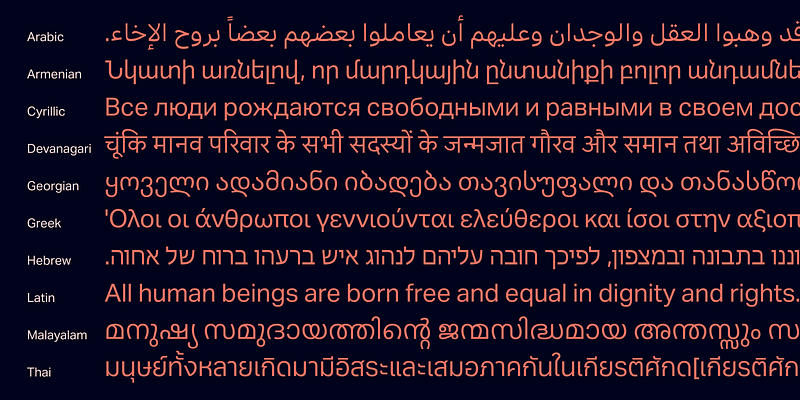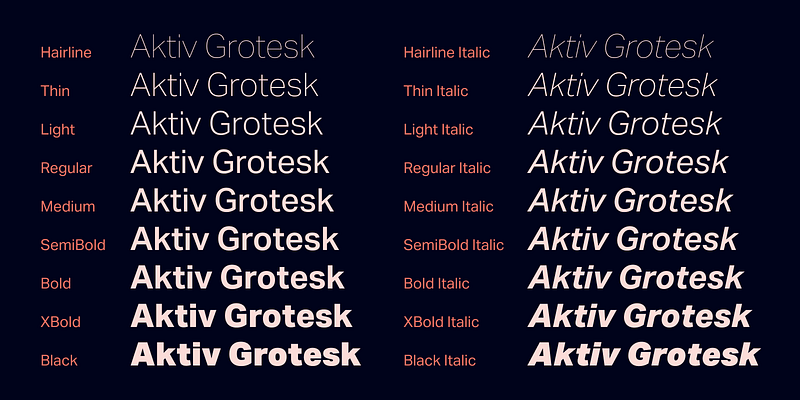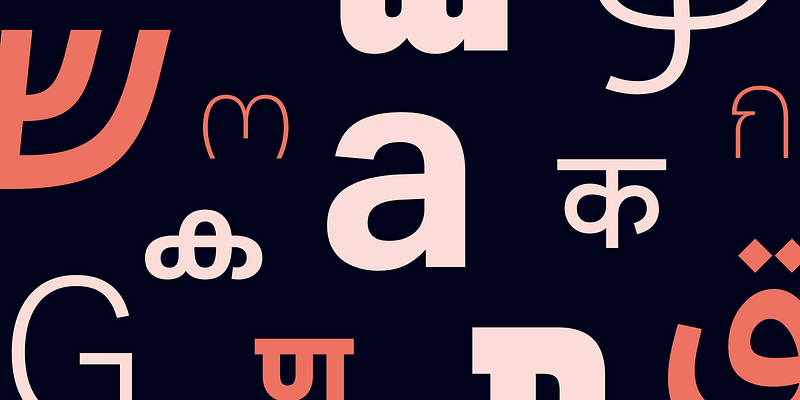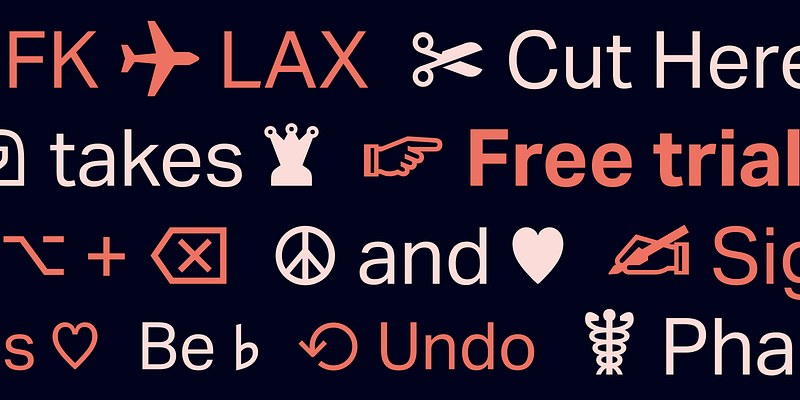
Aktiv Grotesk nimmt eine maßgebliche, aber neutrale Position ein, die jede Botschaft unterstützt, ohne sie zu überlagern. Eine flexible und vielfältige Familie von 24 Stilen mit passenden Kursivschriften, von Hairline bis Black.